35+ ví dụ tuyệt vời về font chữ viết tay trong thiết kế web
Font chữ viết tay (Handwritten font) đã được sử dụng từ rất lâu trong nhiều lĩnh vực với sự phát triển rất đa dạng, và ngày nay đã được áp dụng trong lĩnh vực thiết kế web nhằm mang lại sự độc đáo cho các website.
Font chữ viết tay đã được sử dụng từ rất lâu trong nhiều lĩnh vực với sự phát triển rất đa dạng, và ngày nay đã được áp dụng trong lĩnh vực thiết kế web nhằm mang lại sự độc đáo cho các website. Có rất nhiều kiểu font chữ viết tay độc đáo theo các cách khác nhau, tùy thuộc vào sự sáng tạo và cá tính của những người tạo ra nó. Sử dụng kiểu font chữ này chắc chắn sẽ làm cho thiết kế website của bạn trở nên đặc biệt hơn. Bạn hoàn toàn có thể sáng tạo ra kiểu chữ độc nhất của riêng mình và áp dụng nó vào dự án thiết kế của mình. nó sẽ vô cùng nổi bật.
Trong bài hôm nay, chúng tôi nghĩ đến việc giới thiệu đến bạn những ví dụ tuyệt vời nhất từ các thiết kế web sử dụng font chữ viết tay đẹp mắt. Hãy coi như đây là một nguồn tham khảo cho những ý tưởng thiết kế của bạn. Những website này thực ra khá đơn giản và gần gũi khi dùng kiểu font chữ này. Hãy chọn nó cho dự án thiet ke web hiện tại hoặc sắp tới của bạn và bạn sẽ không phải hối hận vì quyết định của mình.
Ngoài ra, hãy quan sát hướng dẫn thiết kế web của các ví dụ dưới đây và xem cách bố trí các font chữ của họ sao cho hiệu quả nhất. Chúng tôi tn chắc rằng sau khi tham khảo những mẫu web này, bạn sẽ có thiện cảm và ý muốn tìm hiểu sâu hơn về font chữ viết tay trong lĩnh vực thiết kế các website.
1. Celeste Luciano
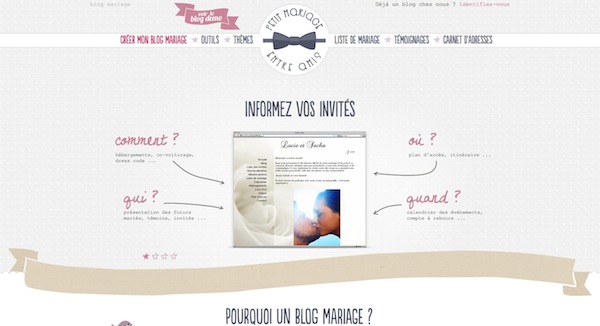
2. Marcello Pisano
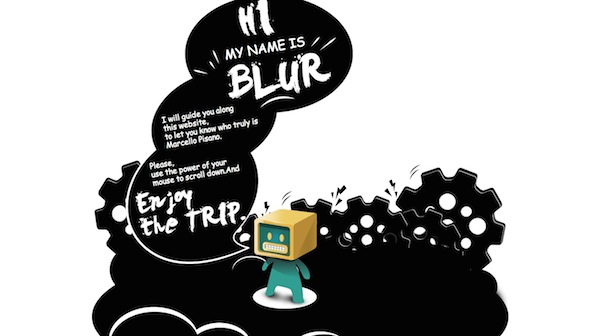
3. Markt
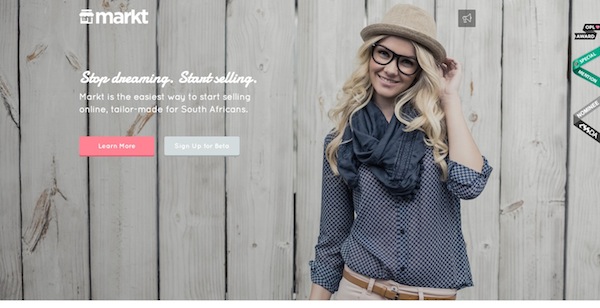
4. Epic
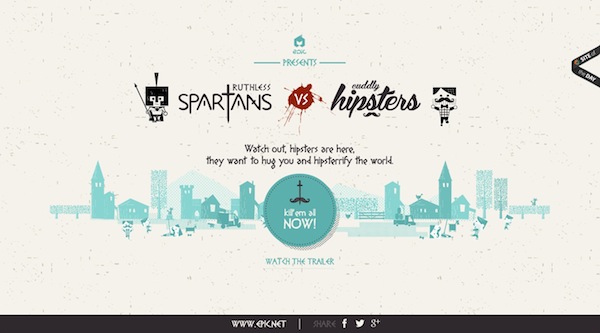
5. PackDog
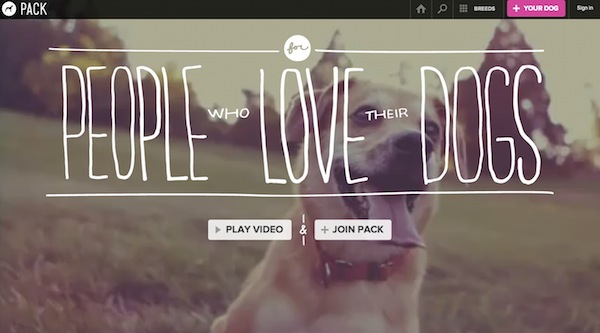
6. First Love
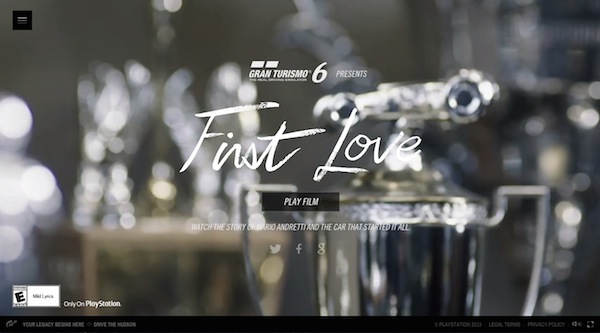
7. The Lifecycle
8. Vintage Hope
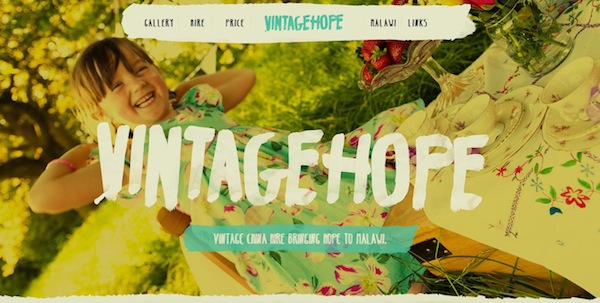
9. SwanSea
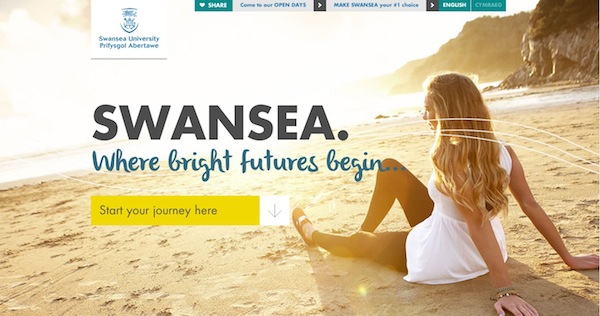
10. Jacquico
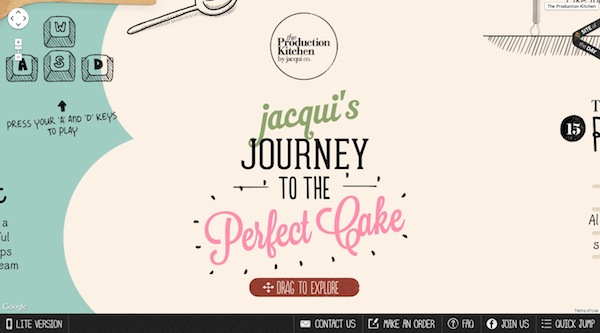
11. Ronaldo Cardoso
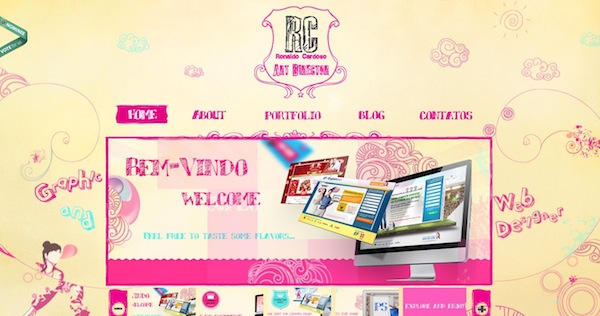
12. Lost My.name
13. Maison Constant
14. Petit Mariage
15. Eat the Ordinary
16. Drink Koa
17. Het Verhaal Van Peter
18. MashVP
19. ServedUK
20. Sarah Ray
21. A Kitchen
22. Ryan W Bock
23. Vince & Marlene
24. The Erasable Wall
25. Prime burger
26. Niky Niky
27. Kinder Fotographie
28. Serve Seattle
29. WinShape
30. AlkoPedia
31. Michel Berger Monkey
32. Javier Guzman
33. Rebecca Sehn
34. The Kings of Summer Movie
35. Space Needle
36. Kreativa Unlimited
37. Poor Remy